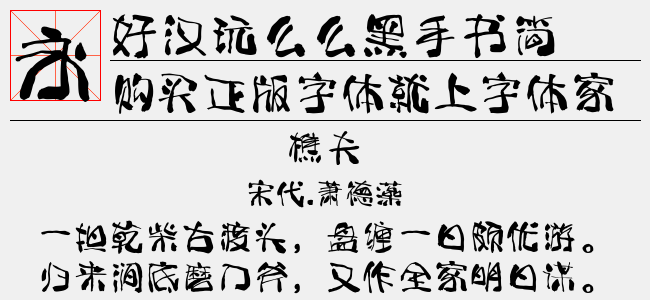
好汉玩么么黑手书简(10.03 MTTF中文字体下载)
好汉玩么么黑手书简 字体大小10.03 M,包含了6763个汉字以及附加其他英文字体和阿拉伯数字,属于锐字字库。好汉玩么么黑手书简(TTF)可以免费下载,商业用途请自行购买版权,它的特征就是艺术,海报,创意,变形,采用安装嵌入的安装方式,支持符号拉丁文日文中文等语言
字体名称:好汉玩么么黑手书简